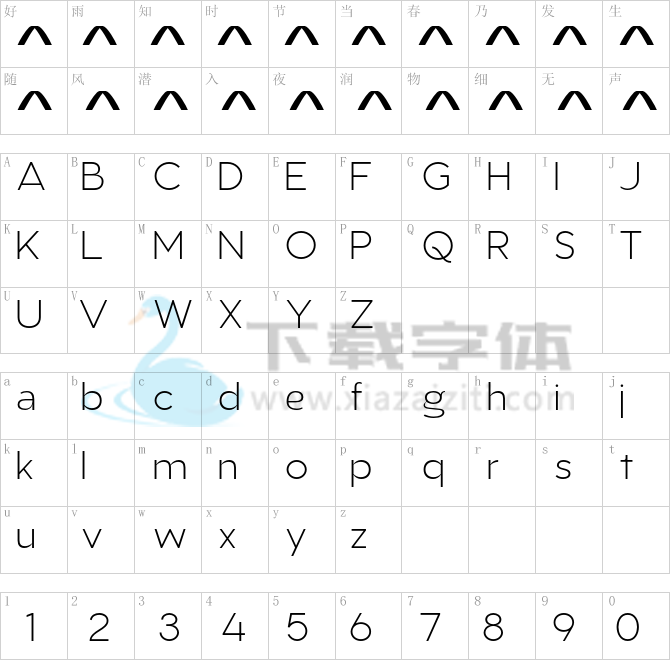
Aukim Light.otf字体下载,这款字体结构工整、笔画清晰,兼顾美观与易读性,适用于标题、正文、海报、包装、LOGO 等多种场景。字形优雅稳定,风格百搭耐看,适配日常排版与创意设计,让文字呈现更舒适、更具质感。Aukim Light.otf字体下载一笔一画,皆是细节,以均衡的比例、流畅的线条打造舒适视觉体验,字形端正大气,风格简约现代。无论是商业设计、品牌宣传还是日常排版,都能轻松驾驭,让文字更有格调与力量。Aukim Light.otf字体下载字体下载。